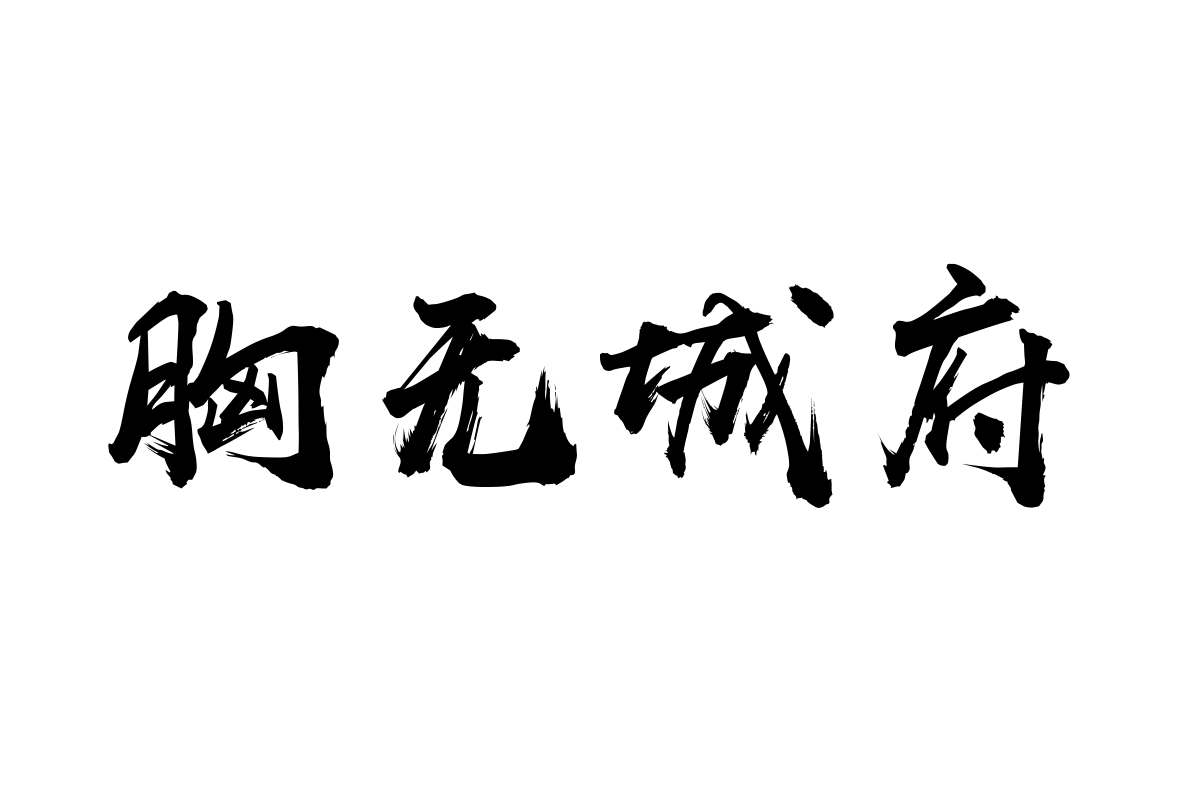
汉仪尚巍手写体是一款专为手写设计,具有独特风格和特色的中文字体。它采用了传统的手写笔触和结构,使得字体既具有现代感又不失传统韵味。
这款字体的特点是笔画流畅自然,线条粗细适中,给人一种优雅而舒适的视觉感受。同时,它的字形结构紧凑,易于阅读和书写,适合用于各种文字设计场景。
此外,汉仪尚巍手写体还注重细节的处理,如字间距、行距等都经过精心调整,使得整体布局更加协调美观。这使得它在印刷品和电子屏幕上都能展现出良好的视觉效果。
总的来说,汉仪尚巍手写体是一款非常适合手写设计的中文字体,无论是用于个人笔记还是商业文档,都能给人留下深刻的印象。